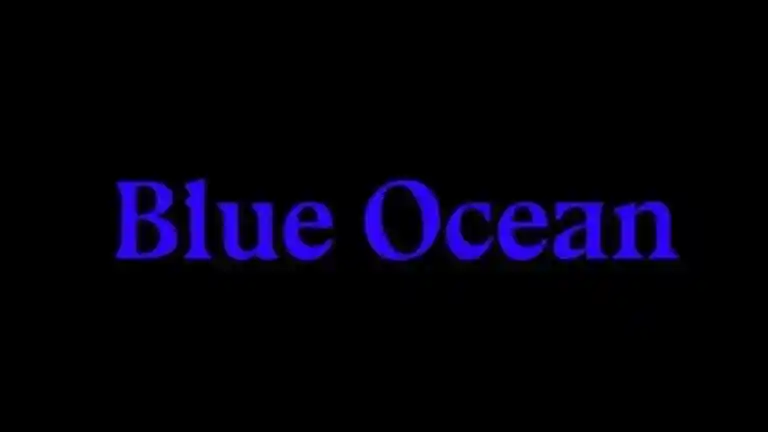
Blue Ocean Serif Font
Introduzimos Blue Ocean Serif Font – uma tipografia serifada moderna e minimalista. Este tipo de fonte é uma versão variável do Bluu Next, criado por Jean-Baptiste Morizot, que Eli Heuer redrew usando curvas de segundo grau. Blue Ocean Serif é perfeito para projetos atuais, seja para estilos de marca, logotipos, convites, design de websites, perfis no Instagram ou cartões de visita. Este tipo de fonte se ajusta a qualquer projeto moderno que você possa estar trabalhando e oferece uma variedade imensa de opções. O seu visual elegante e clean complementará perfeitamente seu próximo trabalho gráfico.